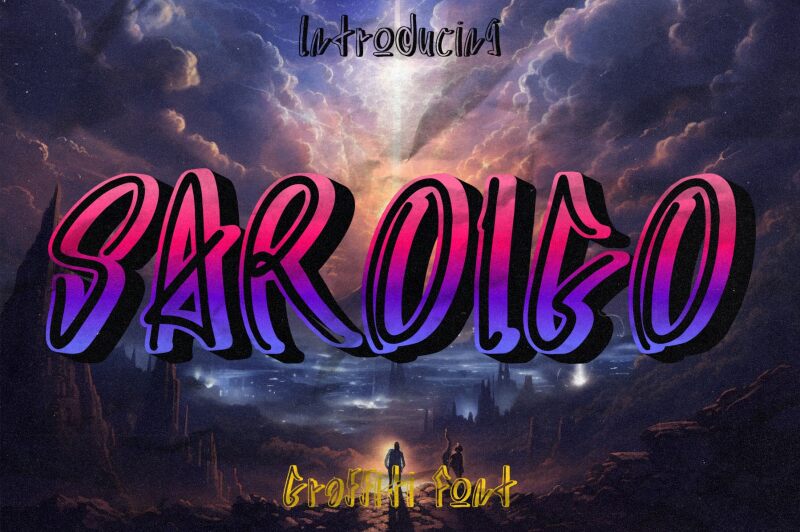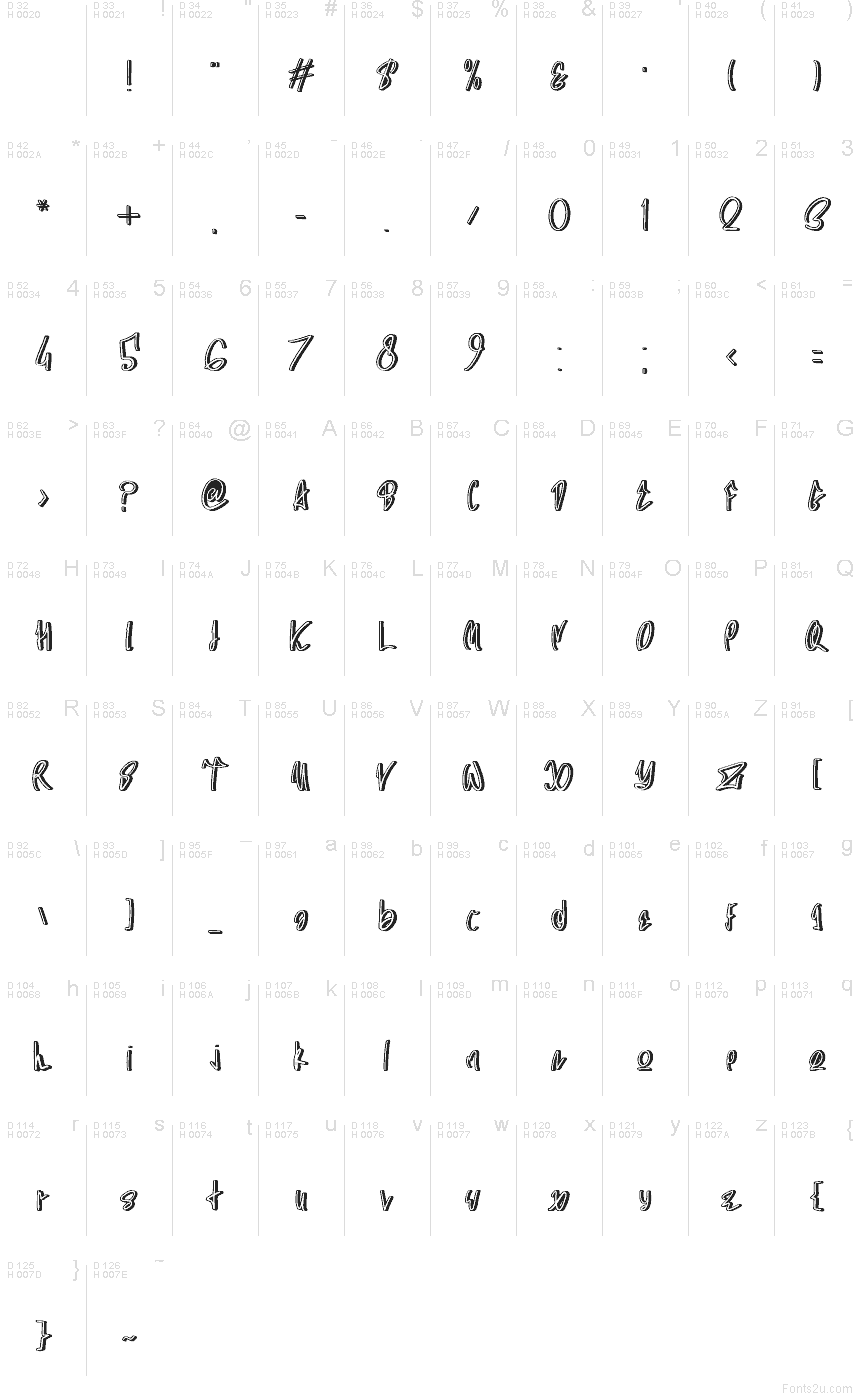
Saroigo od Apeinz je bezplatné graffiti písmo, které definují vysoké smyčkové tvary a živý, ručně kreslený náboj. Silný vnější obrys a úzká vnitřní linka dodávají písmenům efekt fixy, takže celý design působí skicovitě, nafoukle a trochu divoce, spíše než úhledně vyleštěně.
Tahle energie dává smysl na logách streetwearových značek, hudebních letácích, skejtových grafikách, nálepkách a plakátech na akce pro mladé, kde ten nerovnoměrný rytmus dokáže mluvit za vás. Písmo skvěle vynikne i v nadpisech na sociálních sítích nebo na etiketách zboží, zejména pokud hledáte lettering, který vypadá jako rychle „hozený“ na papír, ale přesto si udržuje vizuální řád.